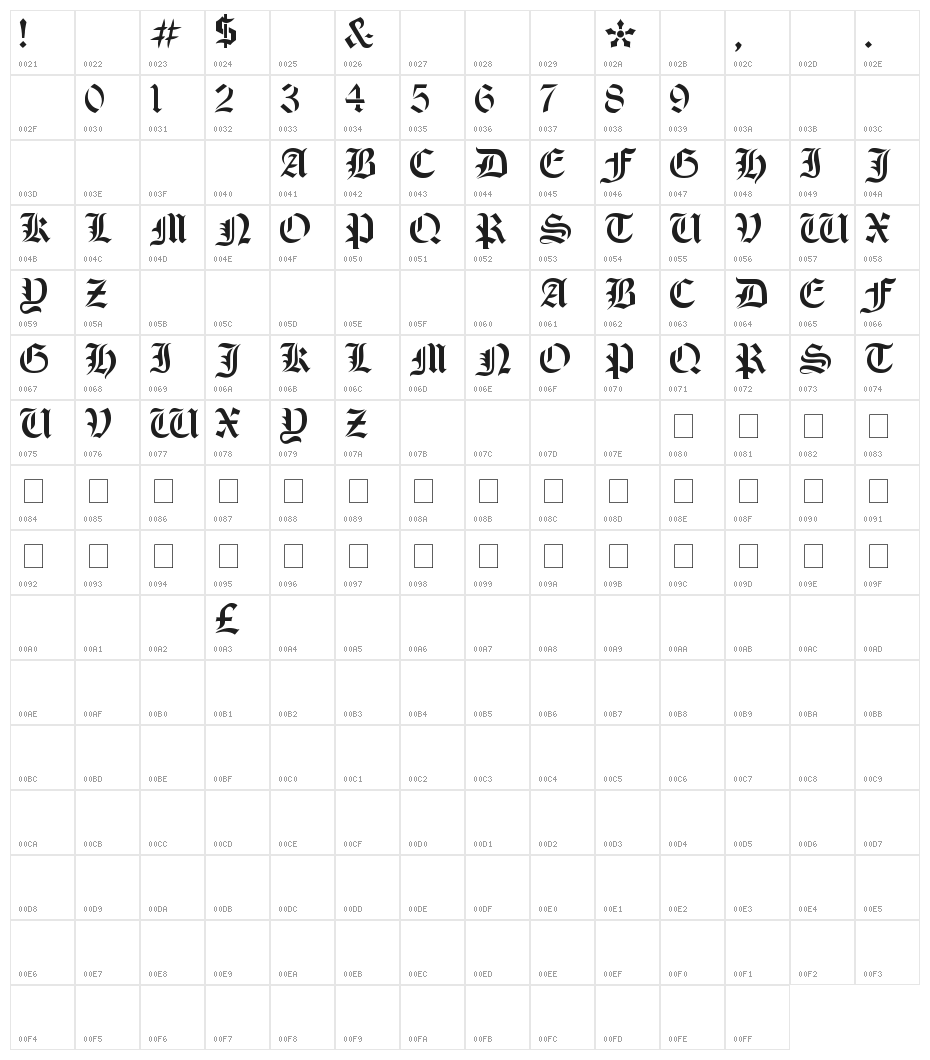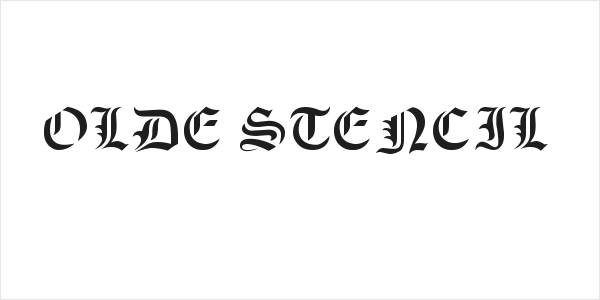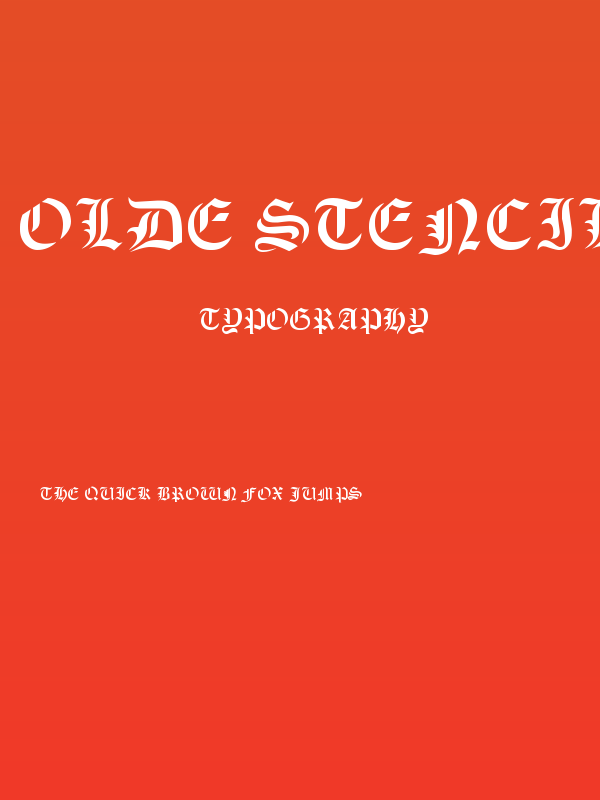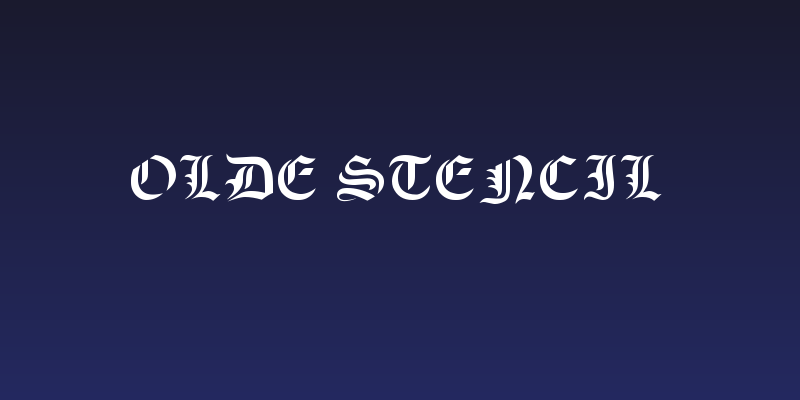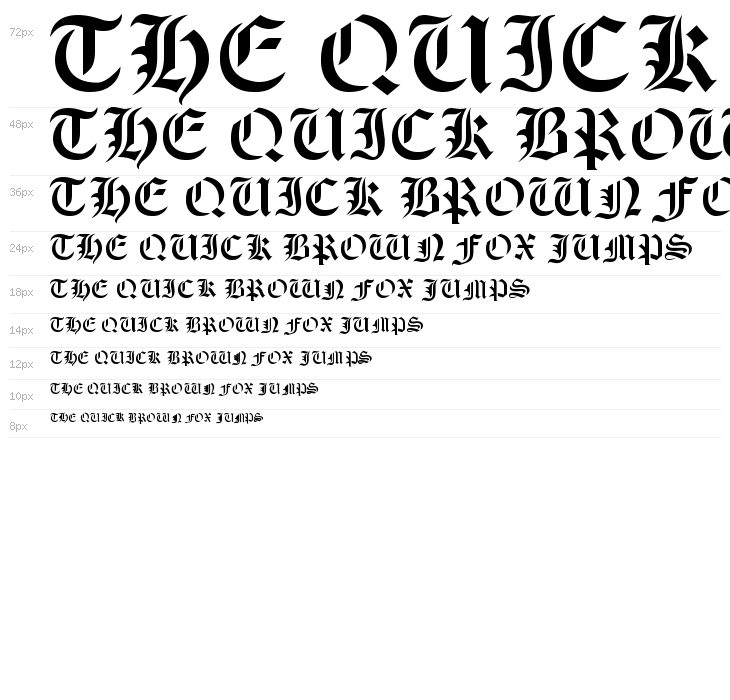
Olde Stencil Font
✎ Gothic
| Proiecte propuse | Ideal for branding, posters, book covers, and any design requiring a bold, historical yet modern look. |